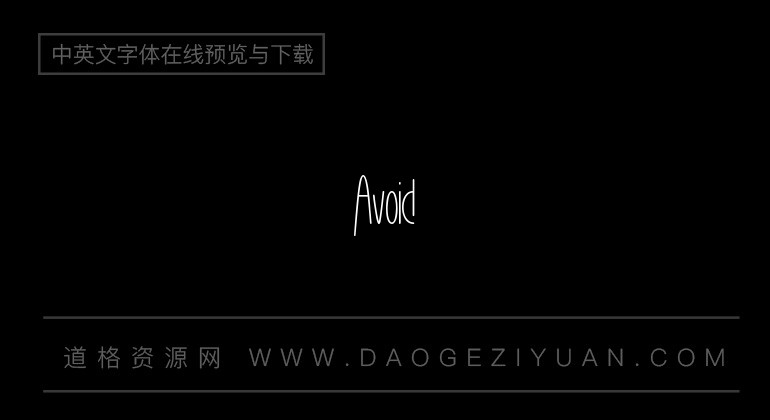
Avoid 字体是一种由著名的设计师和插画家 Tommi Lim 设计的字体,它的特点是非常简洁、干净,同时也非常适合用于广告、海报、商标、标识等设计作品中。这种字体的设计灵感来自于现代主义风格,它的字体线条非常简洁,没有多余的修饰和花纹,非常适合用于需要突出字体本身的设计作品中。 Avoid 字体的设计非常独特,它的字形非常简洁而不失时尚感。它的字母非常流畅,线条之间的间距也非常合适,使得这种字体即使在小号字体上也非常清晰易读。同时,它也非常适合用于不同的设计领域,例如:品牌设计、印刷品、数字媒体等。 总之,如果你正在寻找一种简洁清新、流畅易读的字体,Avoid 字体绝对是一个不错的选择。内容介绍
Avoid是一款非常不错的手写艺术字体,具有很好的视觉感,适合于文化类的宣传设计、商业类品牌的广告和产品包装设计以及个性化文字排版等较多场景。